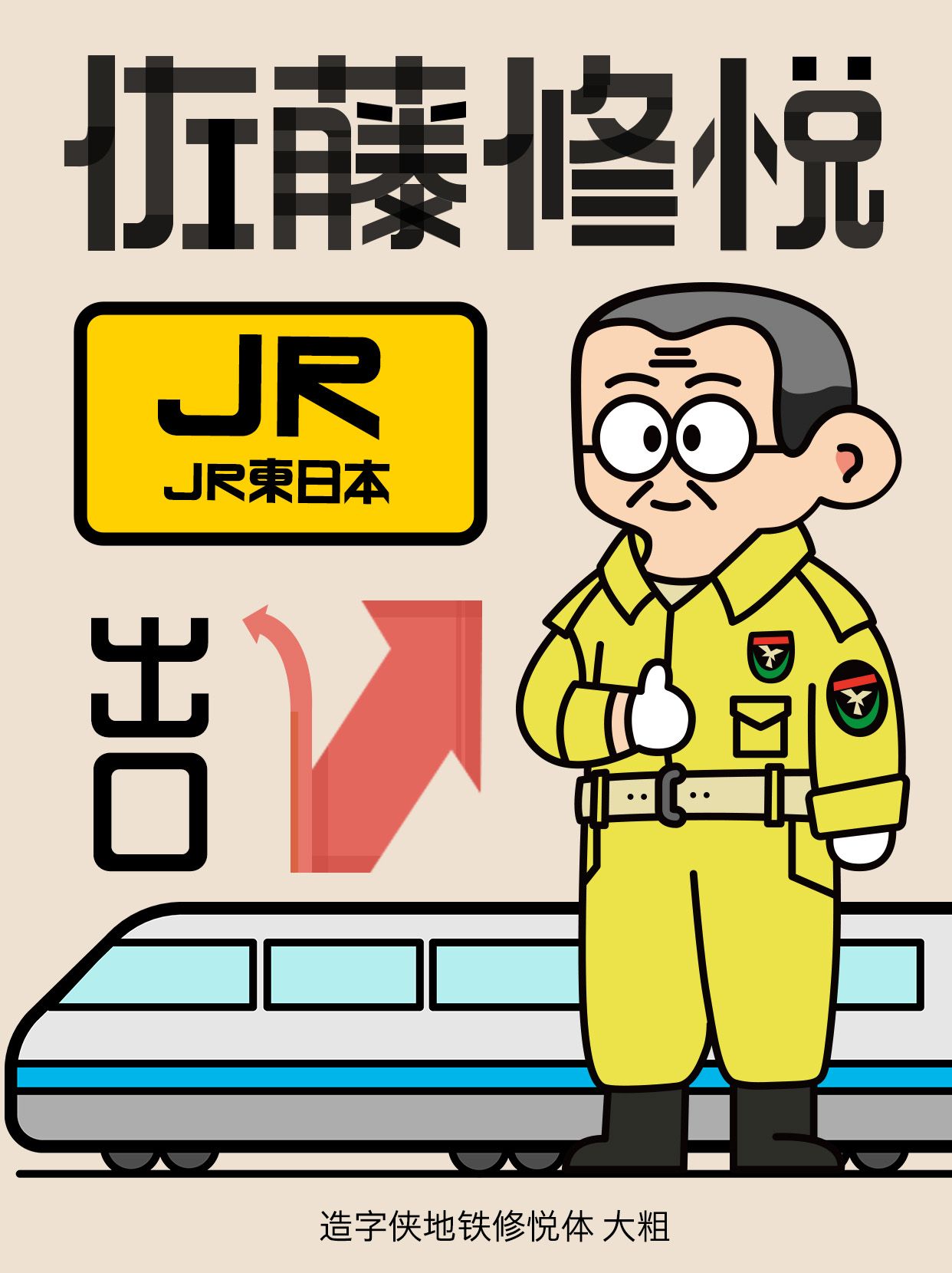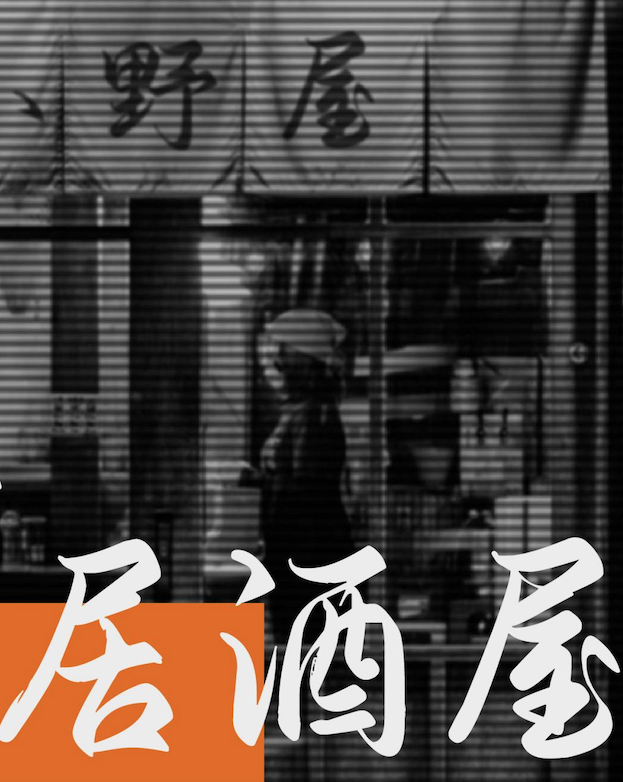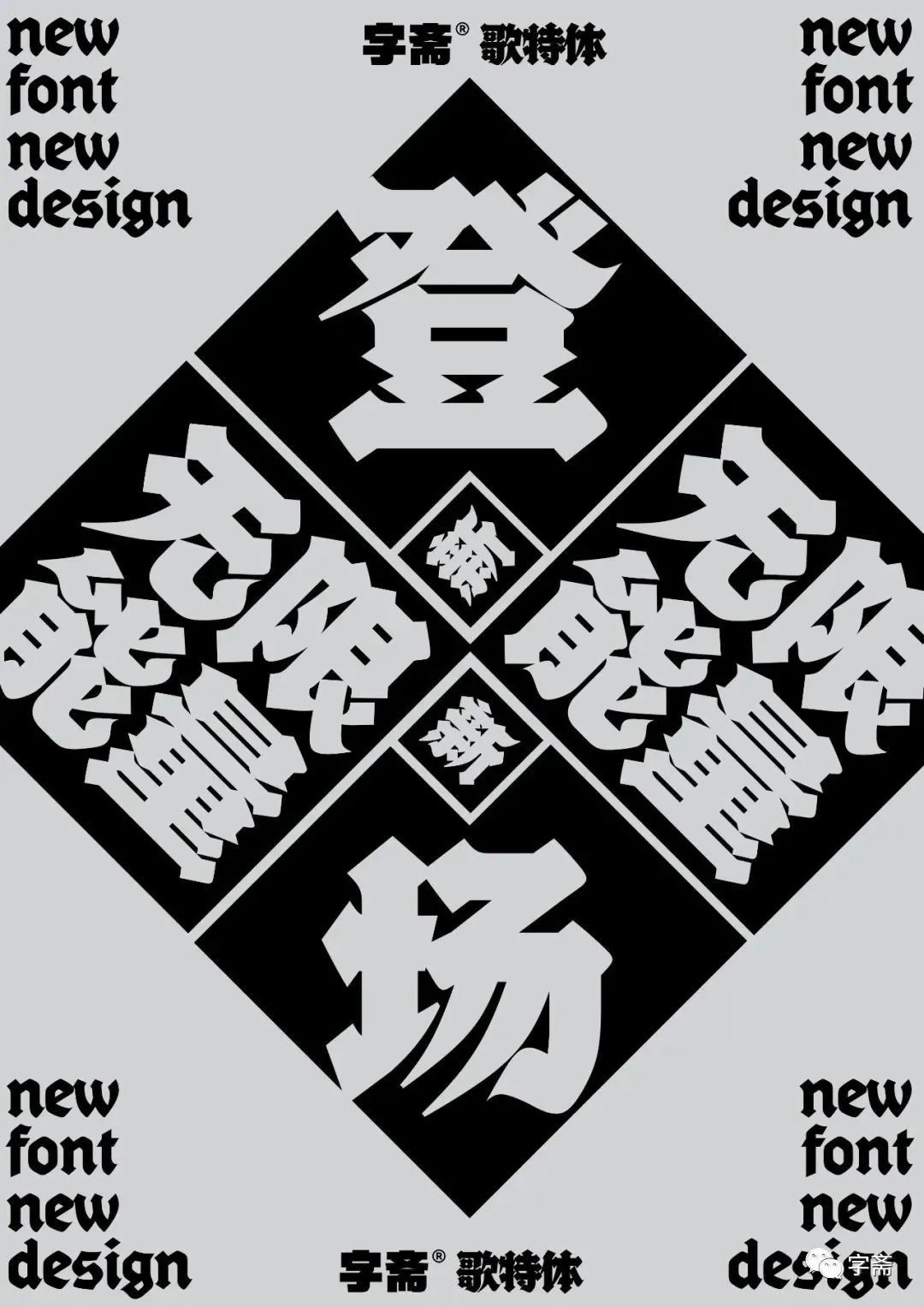
海报字体如何选用?这四款字体让你的海报更吸睛!
在海报设计的广阔舞台上,字体不仅是信息的载体,更是吸引眼球、传达情感的关键元素。选择合适的字体,能让你的海报瞬间脱颖而出,成为视觉焦点。今天,就让我们一起探索四款极具特色的字体,看看它们如何为海报设计增添无限魅力。
1.造字侠热辣隶简
这款字体融合了传统隶书的韵味与现代设计感,笔画粗犷而不失细腻,充满力量与动感。它适合用于音乐节、运动赛事或任何需要展现活力与激情的海报设计中,能够迅速抓住观众的注意力,激发内心的热情与共鸣。
哥特体以其独特的尖锐笔触和强烈的对比效果著称,高手字斋哥特体Pro更是将这一特点发挥到了极致。它适合用于科幻、恐怖或神秘风格的海报设计,营造出一种冷峻、深邃的氛围,让人不由自主地想要探究背后的故事。
3.字圈也字惊鸿行楷
行楷字体以其流畅自然、气韵生动而深受喜爱,字圈也字惊鸿行楷更是将行楷之美演绎得淋漓尽致。它适合用于文艺、旅行或情感类海报设计,能够温柔地传达出细腻的情感与美好的愿景,让观者在欣赏中感受到心灵的触动。
这款字体以其粗犷的笔画和强烈的视觉冲击力而著称,适合用于需要强调力量感、稳定感或现代感的海报设计。无论是商业广告、展览宣传还是城市文化推广,造字侠地铁修悦体 大粗都能以其独特的风格,让海报成为街头巷尾最引人注目的风景线。
综上所述,这四款字体各具特色,适用于不同风格的海报设计。通过巧妙运用这些字体,设计师们可以创造出更加吸睛、更具个性的海报作品,让信息传达更加高效、更加生动。